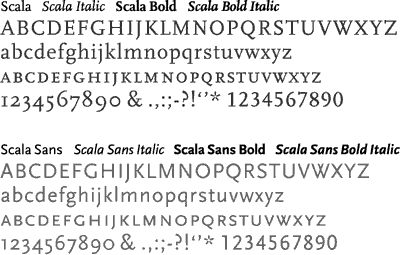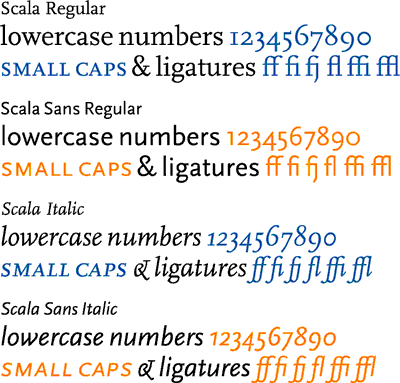
Martin MajoorNascido em 1960, Martin Majoor é o autor do clã de fontes Scala. ScalaLogo que apareceu no mercado, a Scala serifada foi adoptada pelo designer Tony Arefin, para compor publicações de galerias de arte inovadoras, como a galeria londrina Chisenhale. Tanto a versão serifada como a sem serifa sãohoje extensamente usadas no art publishing.